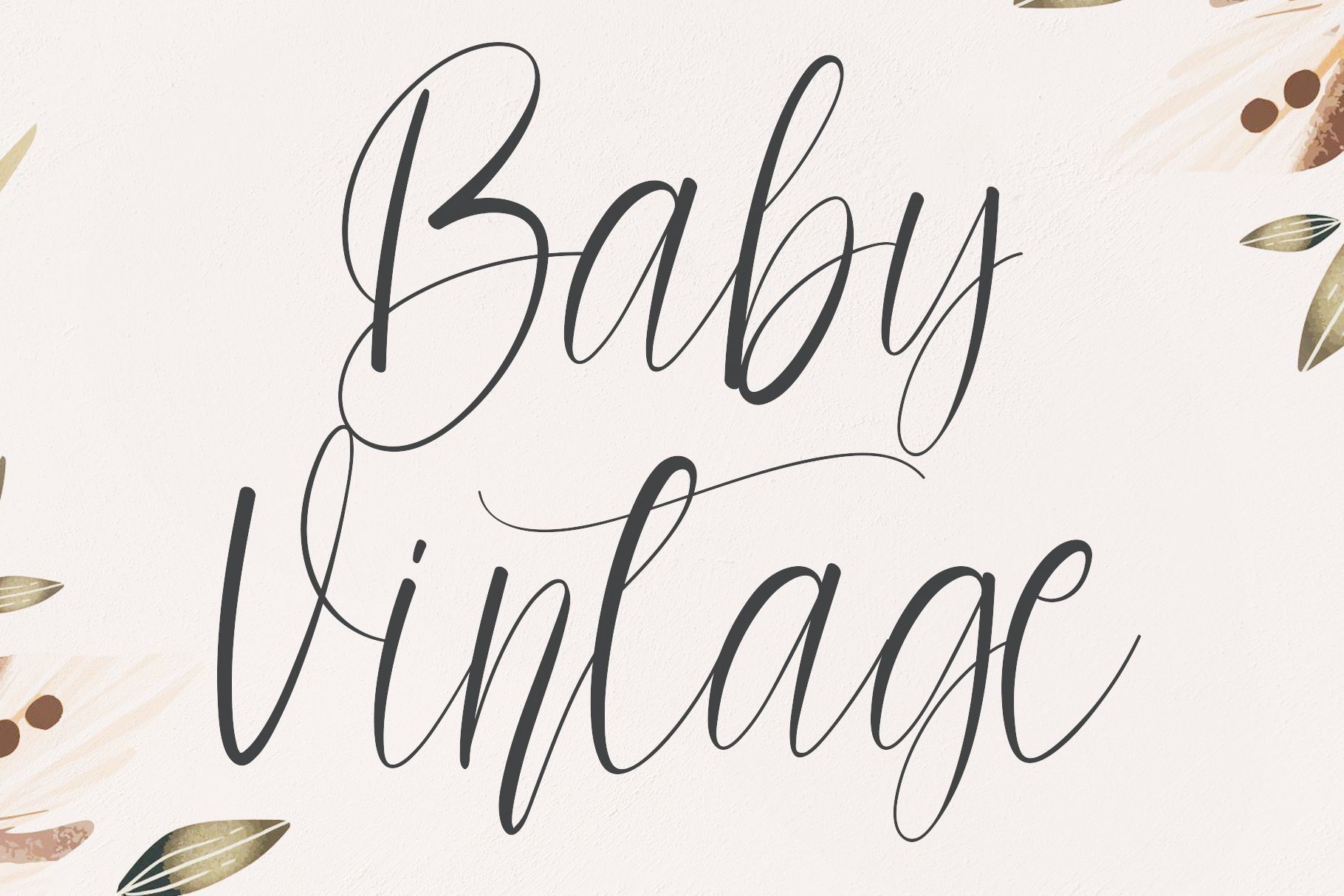
Baby Vintage Font – Download Grátis
Esta é uma fonte script encantadora e estilosa ideal para criar design pessoalizado e romântico. Ideal tanto para escrever convites de casamento quanto cartas e qualquer outro tipo de design que precise de um toque amigável e personalizado, essa fonte traz uma sensação delicada e alegre, complementando perfeitamente designs criados em estilo vintage. Com suas linhas finas e curvas suaves, ela adere-se perfeitamente às tendências atuais sem perder seu encanto vintage. Seja para criar um convite de casamento romântico ou mesmo cartões para aniversários, essa fonte Baby Vintage é uma escolha segura para qualquer designer que busca um toque delicado e elegante em seus projetos. Não deixe de experimentar o charme desta fonte criada por CreativeLetter para trazer ainda mais personalidade aos teus designs!